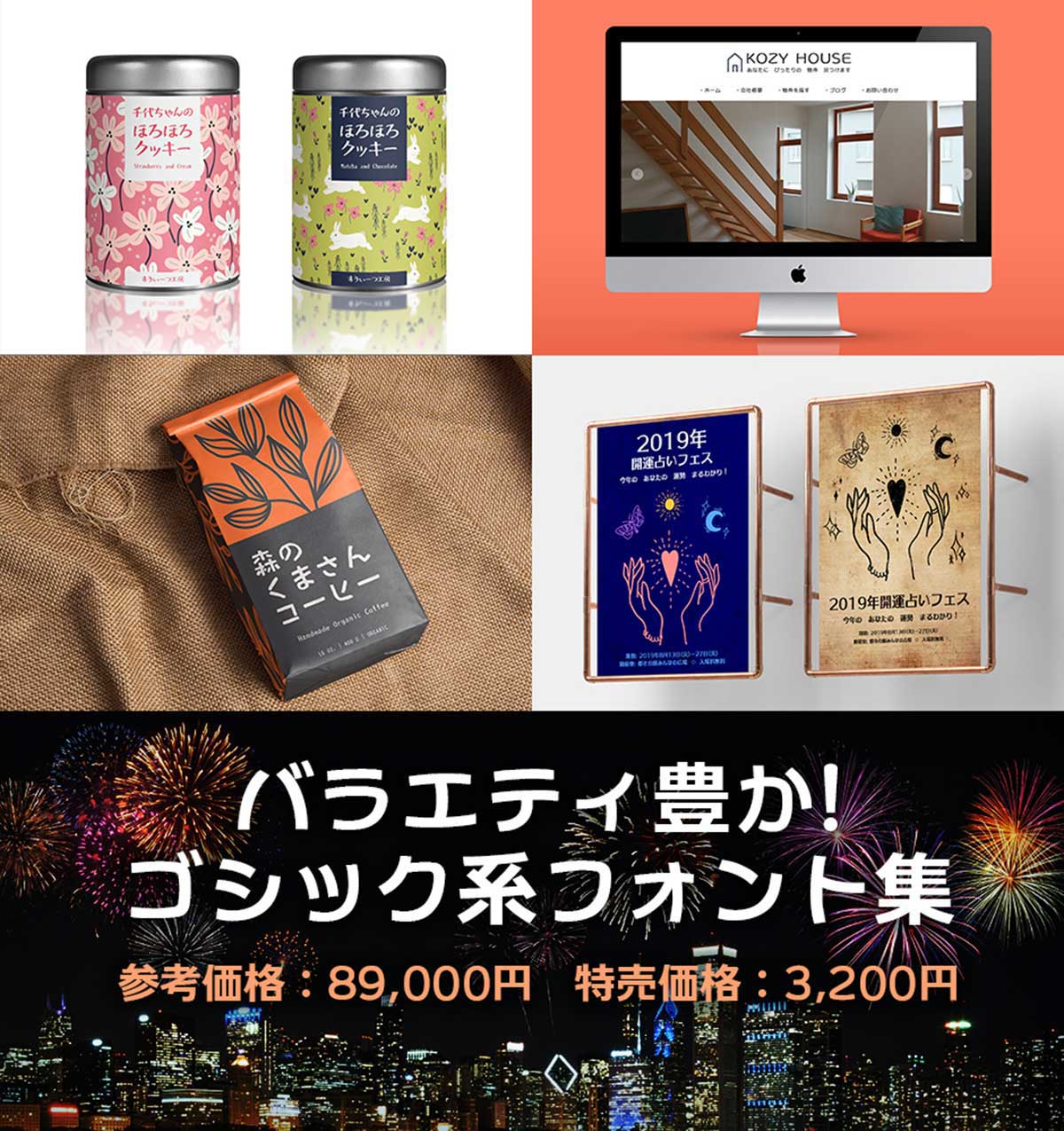
今回は「バラエティ豊か!ゴシック系フォント集」。長文にも使えるベーシックなものからかわいいデザイン系まで合計43書体(通常価格89,000円分)を収録して、3,200円の特別プライス!2週間の期間限定セール中です。
「バラエティ豊か!ゴシック系フォント集」の気になる中身
今回は合計43書体が収録されています。使いやすい日本語ゴシック体フォントをそろえる絶好のチャンスです。
「バラエティ豊か!ゴシック系フォント集」は印刷物や画面表示に対応した可読性にすぐれたフォントが勢揃い
FONTS66スペシャルパック 桜
「Fonts66」は「メイリオ」などのデザインで知られる、デザイナー鈴木竹治氏のフォントブランドで、印刷だけでなく画面表示にも適した可読性の高さが特長です。
個性あふれるポストカードや居酒屋などのメニュー表、web上の画面作成、単調になりがちなデザインのスパイスなどとして幅広くご利用いただけます。